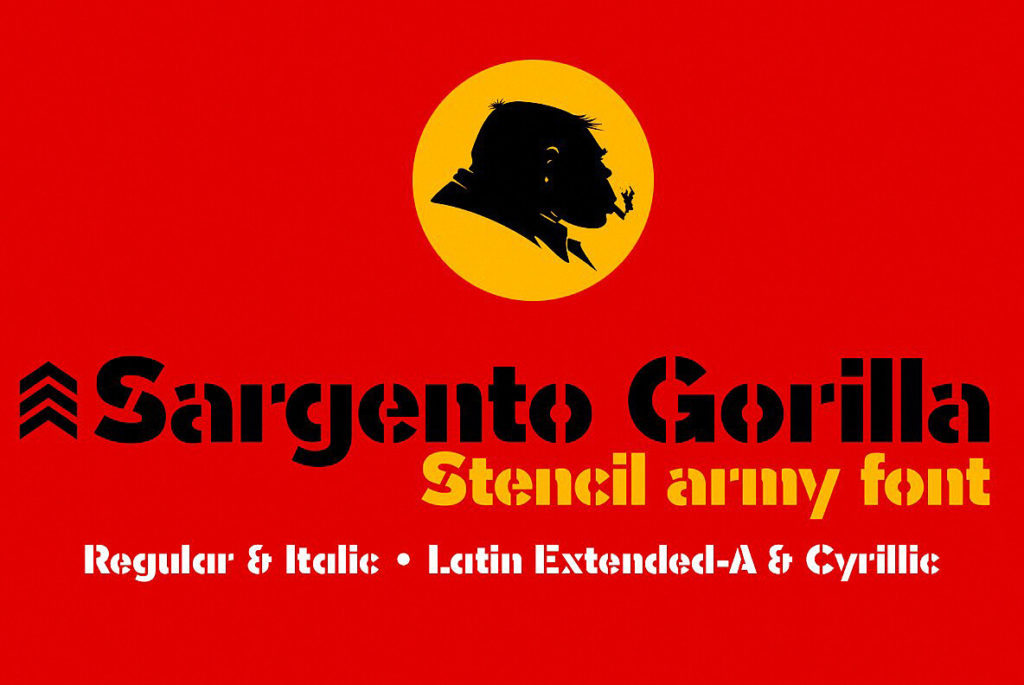
это выразительный декоративный шрифт в стиле военного трафарета (stencil), созданный для передачи брутального и строгого характера. Гарнитура имеет толстые начертания без засечек, что делает её идеальной для крупных заголовков. Шрифт Sargento Gorila поддерживает кириллицу, позволяя использовать его в русскоязычных проектах без потери стиля. В наборе присутствуют специальные символы, включая биткоин и альтернативные глифы. Вы можете скачать бесплатно этот шрифт для личных проектов или приобрести коммерческую лицензию у правообладателя